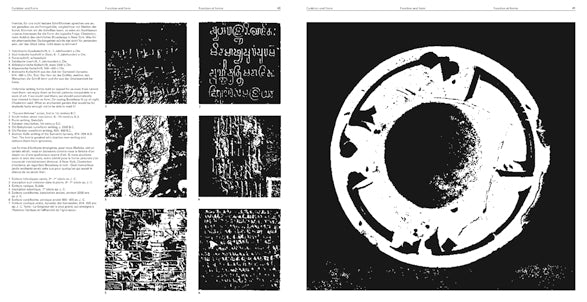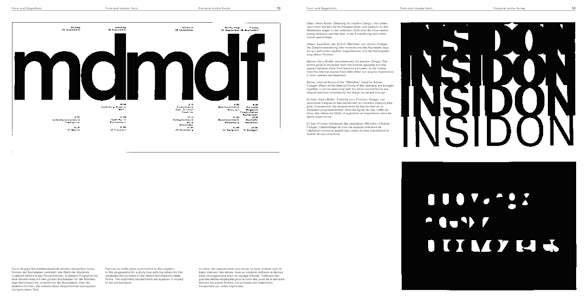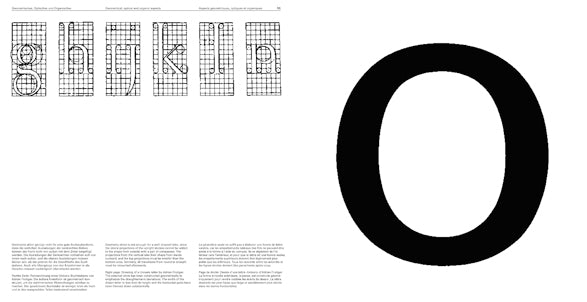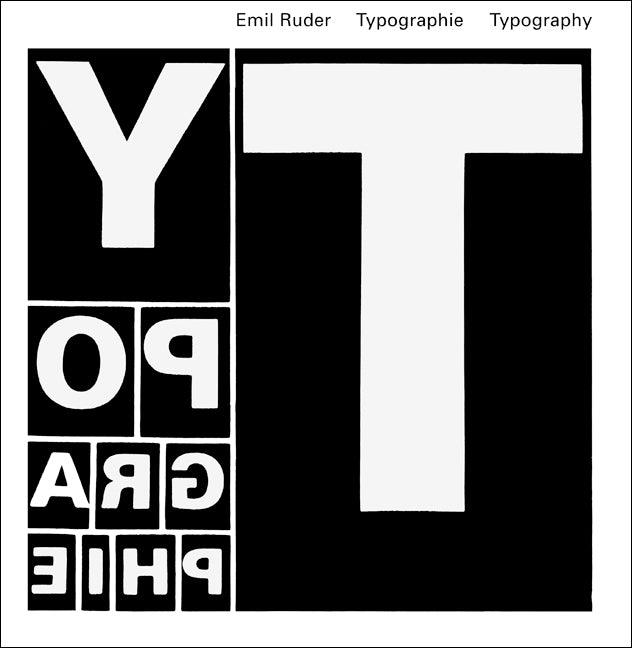
Typographie. Ein Gestaltungslehrbuch
_Grundlagenwerk der modernen Typografie
_Klare Prinzipien zu Ordnung, Raster und Lesbarkeit
_Präzise Beispiele für Schrift, Rhythmus und Proportion
_Prägendes Standardwerk für Ausbildung und Praxis
Dieses Werk ist das Vermächtnis von Emil Ruder, dem Begründer des Swiss Style und einem der einflussreichsten Grafikdesignern der Welt. Als einer der Ersten brach Ruder mit den Regeln der althergebrachten Typografie und schuf neue Gesetze, die den Anforderungen an eine neue Typografie entsprachen.
Die aktuelle Auflage des 1967 erschienenen Werkes ist auch heute noch ein grundlegendes Lehrbuch, auf dem Generationen von Typografen und Grafikern aufbauten und weiterhin aufbauen können. Darüber hinaus vereint es in seinem Gesamtaufbau, den präsentierten Themen, den grafischen Darstellungen und den sich harmonisch einfügenden typografischen Sätzen die Gesamtheit von Ruders Werk. Dieses Buch kann wahrhaftig als ein Meisterstück verstanden werden, von einem der bedeutendsten Männern im Feld des Grafikdesigns und der Typografie.